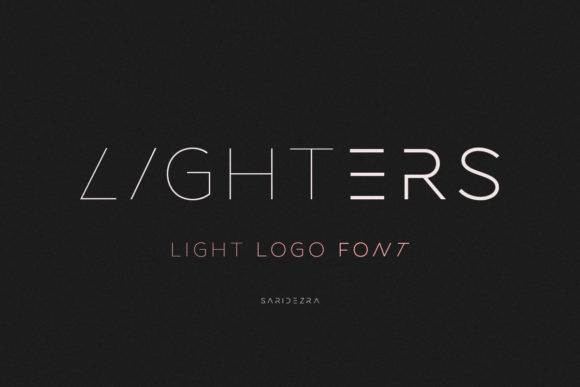
Lighters
Mencari elemen reka bentuk yang sesuai boleh menjadi mencabar, tetapi Lighters menawarkan koleksi luar biasa yang menaik taraf karya anda serta-merta.
Dicipta dengan ketepatan, Lighters menyediakan vektor yang bersih, tipografi yang licin dan lesen komersial untuk ketenangan fikiran.